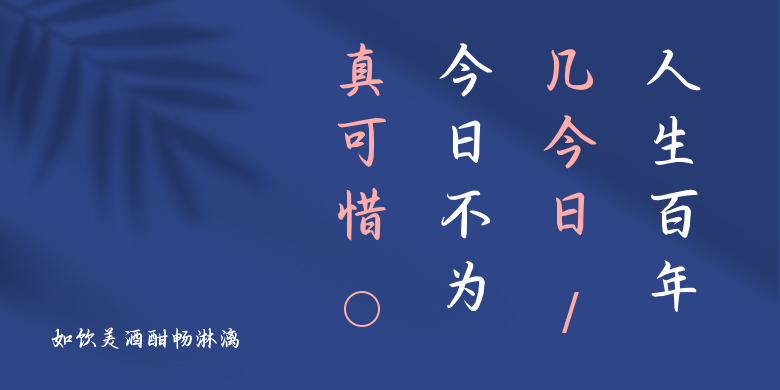
如饮美酒酣畅淋漓
如饮美酒酣畅淋漓,这款字体结构工整、笔画清晰,兼顾美观与易读性,适用于标题、正文、海报、包装、LOGO 等多种场景。字形优雅稳定,风格百搭耐看,适配日常排版与创意设计,让文字呈现更舒适、更具质感。如饮美酒酣畅淋漓一笔一画,皆是细节,以均衡的比例、流畅的线条打造舒适视觉体验,字形端正大气,风格简约现代。无论是商业设计、品牌宣传还是日常排版,都能轻松驾驭,让文字更有格调与力量。如饮美酒酣畅淋漓字体下载。